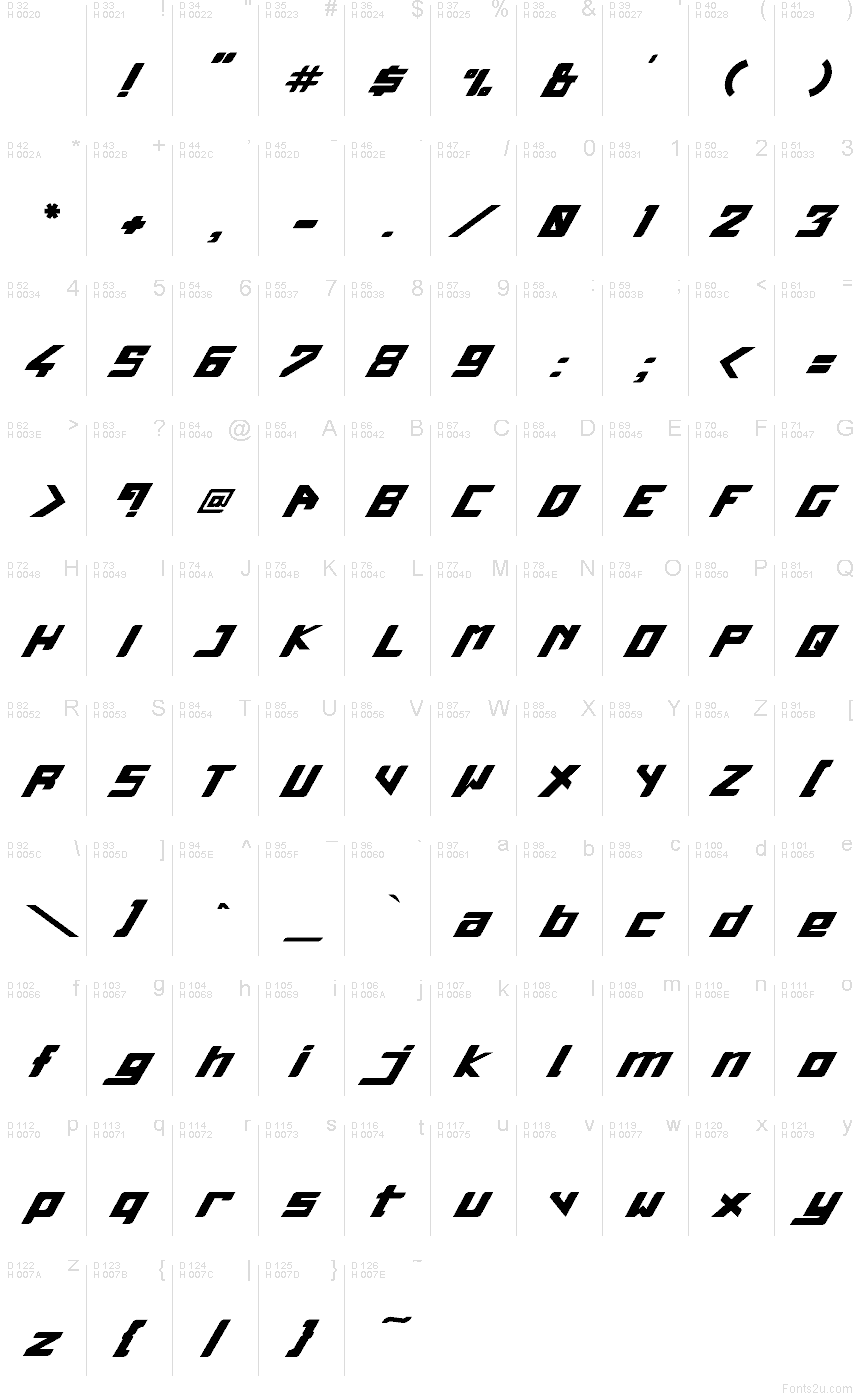
It's a Jump
It's a Jump od Roozbeha Ebadiho je bezplatné techno písmo typu display s ostrými sklonmi a vyrezávanými tvarmi, vďaka ktorým písmená pôsobia rýchlo a hranato. Tvary zostávajú jednoduché a kompaktné, no vďaka zrezaným rohom a dlhým diagonálnym ťahom má celá rodina svižný, futuristický rytmus.
It's a Jump sa výborne hodí na herné logá, nadpisy plagátov, pozvánky na podujatia, motion grafiku a obaly, kde je žiadaný úderný technologický štýl. Jeho naklonená štruktúra a rezané detaily sa tiež skvele hodia na akcenty v nadpisoch, produktové etikety a digitálnu grafiku, ktorá potrebuje výrazný geometrický nádych bez zbytočných dekorácií.
Obsahuje kurzívu.